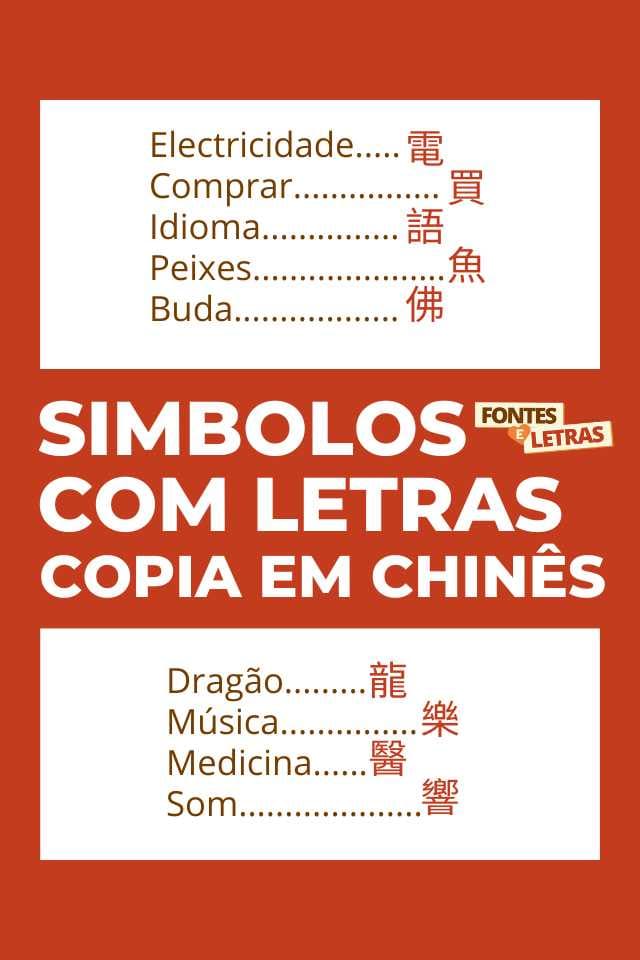
Letras Chinesas para Copiar (Estilo Chinês)
As letras chinesas são caracteres para copiar e colar no nome, no nick, na bio ou como ideia de tatuagem. São caracteres com visual de escrita chinesa, perfeitos pra deixar o nick com aquele ar oriental. Escreva o seu texto na caixa lá em cima pra ver o seu nome no estilo chinesa, ou copie direto da tabela abaixo.
O que são as letras chinesas?
As letras chinesas aqui são caracteres Unicode que imitam o visual da escrita chinesa (como 卂乃匚). Não são chinês de verdade — são símbolos decorativos que deixam o seu nome com estilo oriental, muito usados em nicks de jogos.
💡 Dica: como não é chinês real, não tente traduzir. A ideia é o visual: monte o seu nome letra por letra com a tabela.
Tabela de letras estilo chinês
Cada letra latina vira um caractere de estilo chinês:
| Latina | Estilo chinês | Latina | Estilo chinês |
|---|---|---|---|
| A | 卂 | N | 几 |
| B | 乃 | O | ㄖ |
| C | 匚 | P | 卩 |
| D | ᗪ | Q | Ɋ |
| E | 乇 | R | 尺 |
| F | 千 | S | 丂 |
| G | Ꮆ | T | ㄒ |
| H | 卄 | U | ㄩ |
| I | 丨 | V | ᐯ |
| J | フ | W | 山 |
| K | Ҝ | X | 乂 |
| L | ㄥ | Y | ㄚ |
| M | 爪 | Z | 乙 |
Usos das letras chinesas
- Tatuagem — teste como fica a frase antes de tatuar (veja fontes para tatuagem).
- Nick e perfil — um nome diferentão nos jogos e redes.
- Decoração e arte — posts, convites e desenhos.
As letras chinesas são chinês de verdade?
Não. São caracteres Unicode que imitam o visual da escrita chinesa, para usar como estilo em nicks e nomes. Não têm tradução.